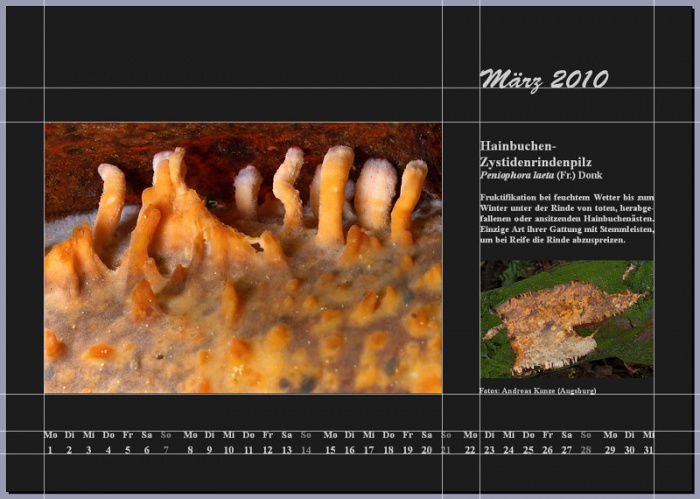
Lizenz für BarcBrushDB Bold?
mein Name ist Andreas Kunze, ich betreibe die private Website www.entoloma.de und suche Rat in einer Font-Frage:
Vor einigen Jahren habe ich ein Kalenderblatt entworfen und möchte das Ganze jetzt als kostenlose Vorlage auf meiner Seite zum Download anbieten. Das Layout beinhaltet den Font "BarcBrushDB Bold", mit dem ich den Monat und das Jahr formatiert hatte. Leider finde ich im Web keine Infos über die Lizenz. Als Urheber tauchen eine PrimaFont GmbH sowie Christine Mauerkirchner und Rainer Grunert auf. Der Font kann zwar kostenlos auf diversen Sites heruntergeladen werden, ich bin mir aber unschlüssig, ob das legal ist.
Der Font scheint ein Klon der Brush Script von Robert E. Smith zu sein, ob der Klon auf legale Weise zustandegekommen ist, läßt sich ohne weitere Informationen zur BarcBrush schwer sagen, wahrscheinlich ist es nicht.
Jenseits der rechtlichen Frage denke ich aber, daß es ästhetische Gründe gibt, über eine andere Schrift nachzudenken. Mit Times und Brush wird der Kalender immer gebastelt und unprofessionell wirken.
Jepp, man kann jetzt streiten, ob der Anbieter (Primafont) überhaupt gültiger Rechtsinhaber ist, aber prinzipiell ist das KEIN Freeware-Font, sondern die Schrift wurde einfach als Raubkopie ins Netz gestellt. Eine Weiterverbreitung in einer Kalendervorlage wäre somit nicht zulässig.